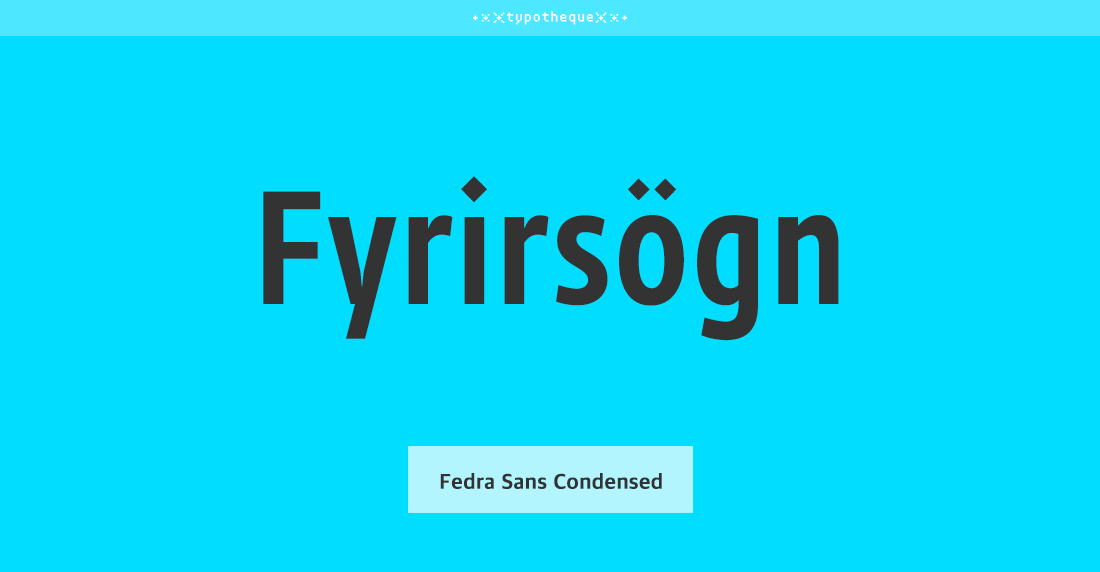
- Fedra Sans Condensed Std는 인쇄를 목적으로 만들어졌으며 차별화 된 자폭으로 인해 주로 복잡한 텍스트를 만들 때 유용하다.
또한 이 폰트를 사용함으로써 공간을 절약하는 효과도 볼 수 있다.
폰트 정보 폰트명 Fedra Sans Condensed Std 구분 고딕 디자인디렉팅 Peter Biľak 출시년도 2006